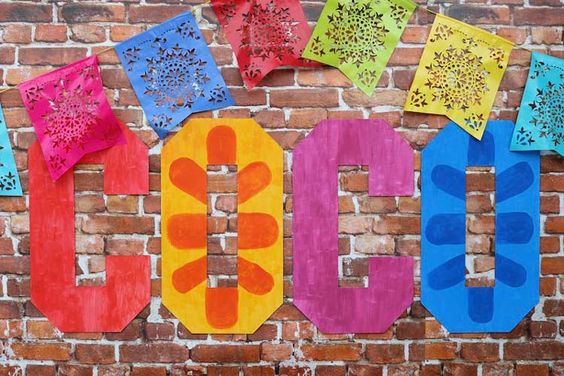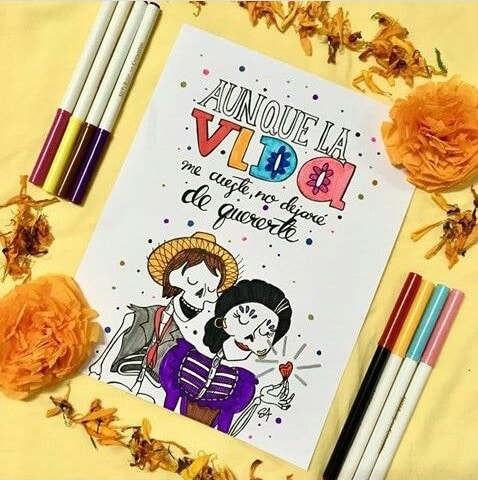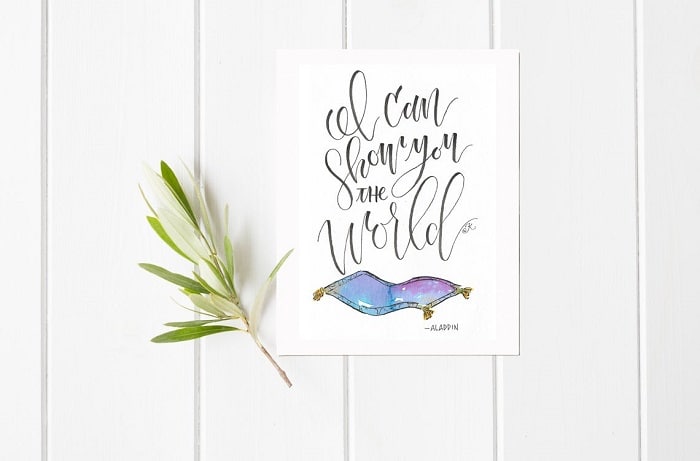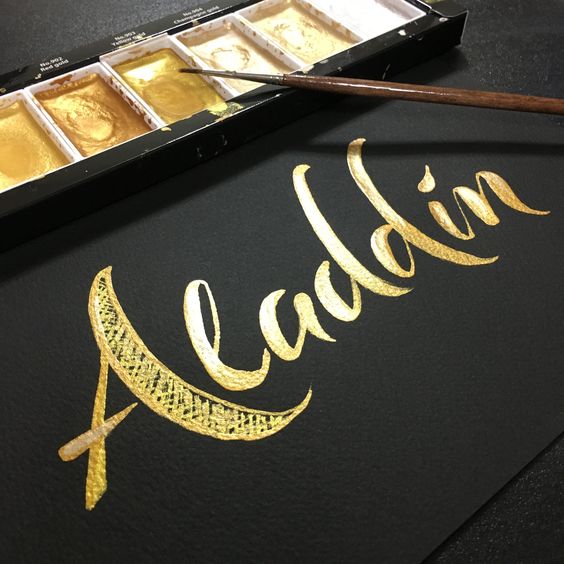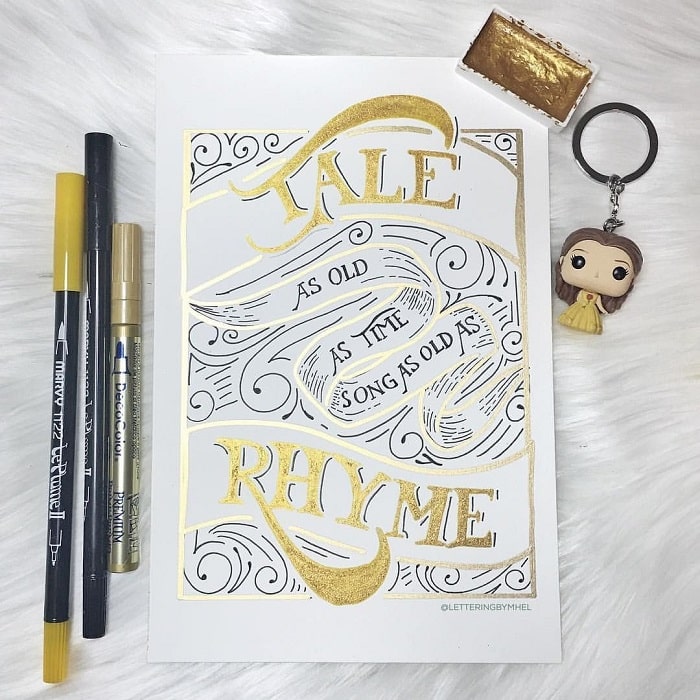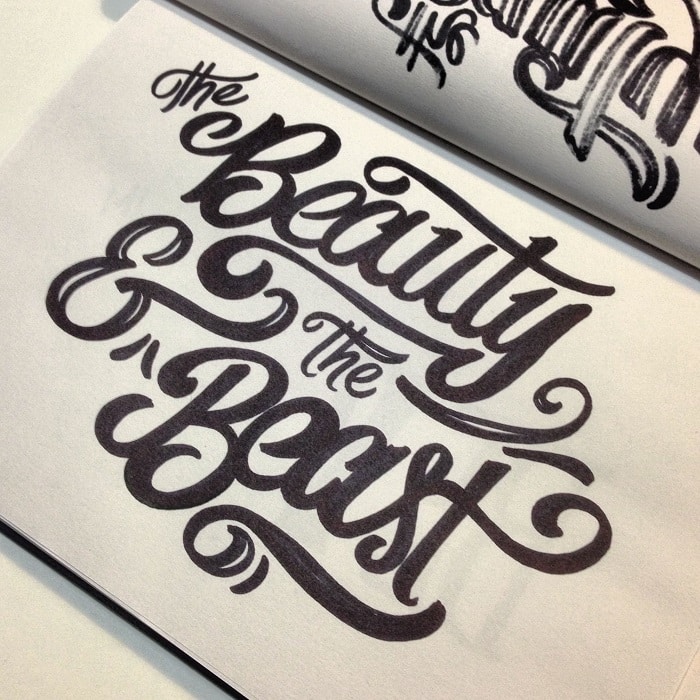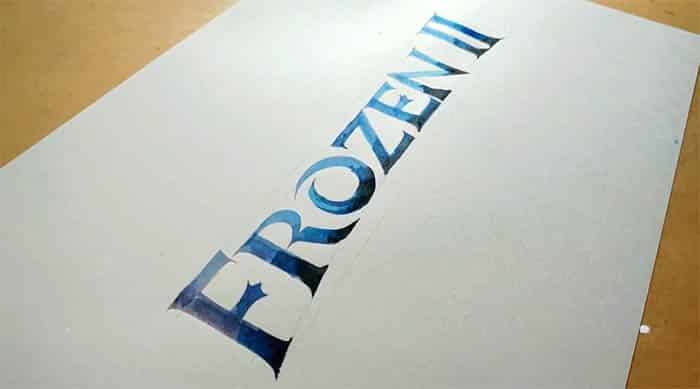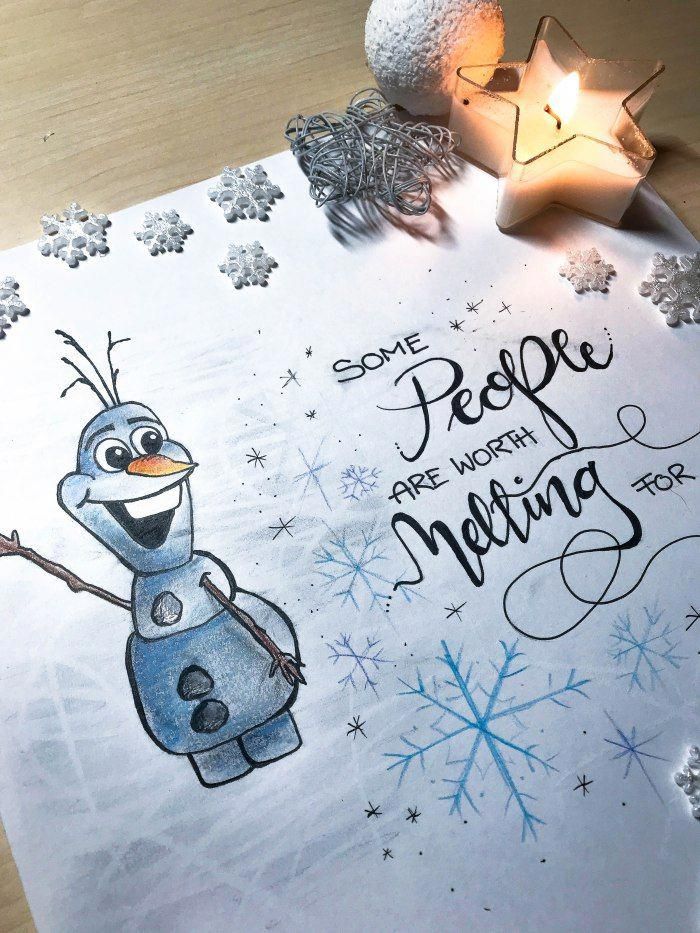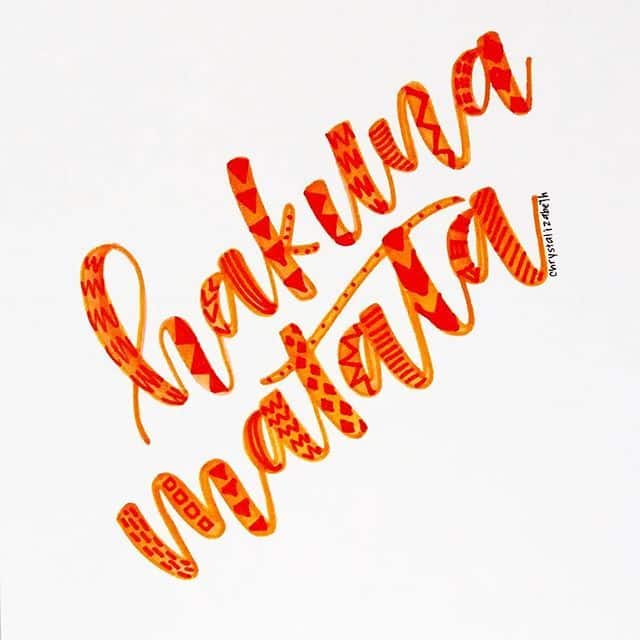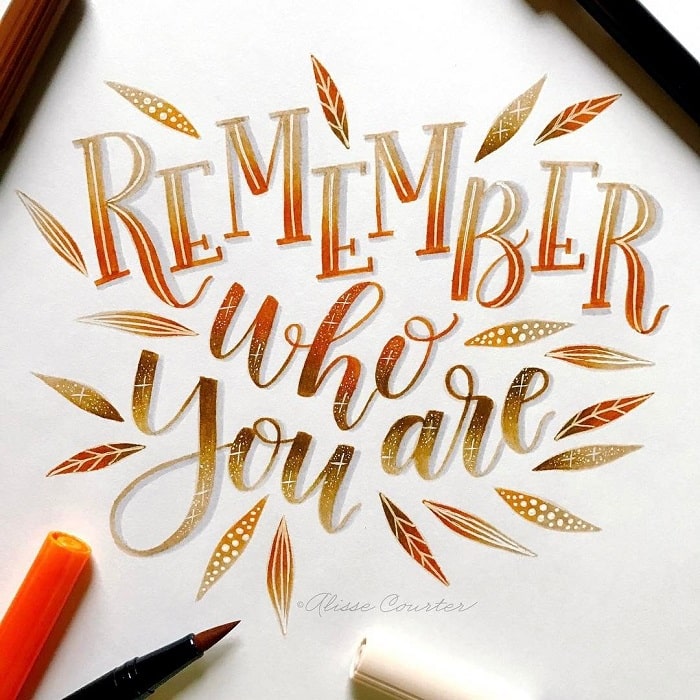
Si sois unos enamorados de las películas de Disney, seguro que en muchas ocasiones os han venido ganas de realizar un hand lettering con las letras de los carteles de vuestras películas favoritas, como «El Rey León«, «Coco«, «Cars«, «Lilo & Stich«, «Moana«, entre muchas otras. Si os fijáis, las tipografías de esos carteles son maravillosas y, de todas todas, comunican la esencia y el estilo de la película.
En el caso de que queráis dibujar las letras del cartel, no tenéis más que copiarlas. Sin embargo, si queréis escribir otro mensaje con esas letras pero se os dificulta la tarea, podéis descargar las fuentes Disney para instalarlas en vuestro ordenador y así poder escribir cualquier mensaje o frase y dibujarlas en papel copiándolas de la fuente, al igual que si queréis hacer el diseño para un tatuaje de Disney o de otro estilo, podríais buscar las fuentes para tatuajes en Internet y descargároslas para ver cómo quedan con la palabra o frase escogida.
A continuación os voy a mostrar algunos hand letterings de películas Disney que son una maravilla y que podéis hacerlos vosotros también con el truco que os hemos dado o inspirándoos en los colores y en el estilo de cada película.
Letterings de El Rey León
Empezamos por «El Rey León», sin duda una de esas películas Disney que marcan la infancia. Las letras del cartel son letras romanas mayúsculas, sin embargo, podéis realizar otras creaciones con frases míticas de la película, como «Remember who you are» («Recuerda quién eres») o «Hakuna matata». El estilo de estos hand letterings puede ser variado, lo que sí que les queda bien con los colores tierra, los verdes camuflaje, los naranjas y los amarillos. También lucen muy bien los estampados de tipo tribal y completar el hand lettering con algunos dibujos de hojas o árboles de la sabana.
Letterings de Aladdín
¡Ay, Aladdin! Una de mis películas favoritas desde pequeña, la película que me enseñó a amar al mundo árabe y a los espíritus libres. Sin duda, hay un hand lettering maravilloso que no falla: dibujar las letras de Aladdin igual que las del cartel, que simulan ser hojas de sables, utilizando un color dorado que, sobre negro, aún funciona mejor. Otra idea es tomar una frase mítica de la serie, como «I can show you the world» («Te puedo enseñar el mundo») que es la primera frase de la canción «A Whole New World«, más conocida en español como «Un mundo ideal» con un tipo de letra romántica y añadiendo un dibujo de una alfombra mágica.
Letterings de Frozen
«Frozen» es otra de las películas Disney que ha entrado en nuestros corazones hace pocos años y ha sido para quedarse. Si queréis dibujar las letras del cartel, son unas mayúsculas bastante gruesas con pequeños remates afilados que simulan trozos de hielo. Las podéis pintar en tonos azules con un degradado. En la película hay un simpático muñeco de nieve que se llama Olaf y que tiene una frase que se quedó para la posteridad: «Some people are worth melting for«, es decir, «Hay personas por las que merece la pena derretirse». Me parece una frase perfecta para un hand lettering que simule una caligrafía moderna y con dibujos sencillos de copos de nieve.
Letterings de Coco
Coco… una de las películas más bonitas y emtoivas de Disney que he visto últimamente. Te hace amar de veras la cultura mexicana, en especial el culto a los muertos. Su tipografía es absolutamente maravillosa, llena de colores vibrantes y de decoraciones sencillas que recuerdan a los adornos de El Día de los Muertos. Simplemente si queréis dibujar y pintar las letras de Coco, lucirá genial. Si os apetece más escoger una frase como la de la canción «Aunque la vida me cueste no dejaré de quererte«, podéis mezclar varios tipos de letra y ahcer que una destaque con las letras del cartel, en este caso, «VIDA».
Letterings de La Bella y la Bestia
No podíamos irnos sin mencionar a «La Bella y la Bestia», otra historia de amor que nos hizo suspirar y aprender que «la belleza está en el interior». La tipo del cartel es una letra alta y alargada, que recuerda algo a las de estilo modernista, con finos remates elegantes y en color dorado. Sin embargo, para los hand letterings de esta película se pueden escoger otro tipo de letras, como las que vemos en estos dos ejemplos, pero siempre con florituras.